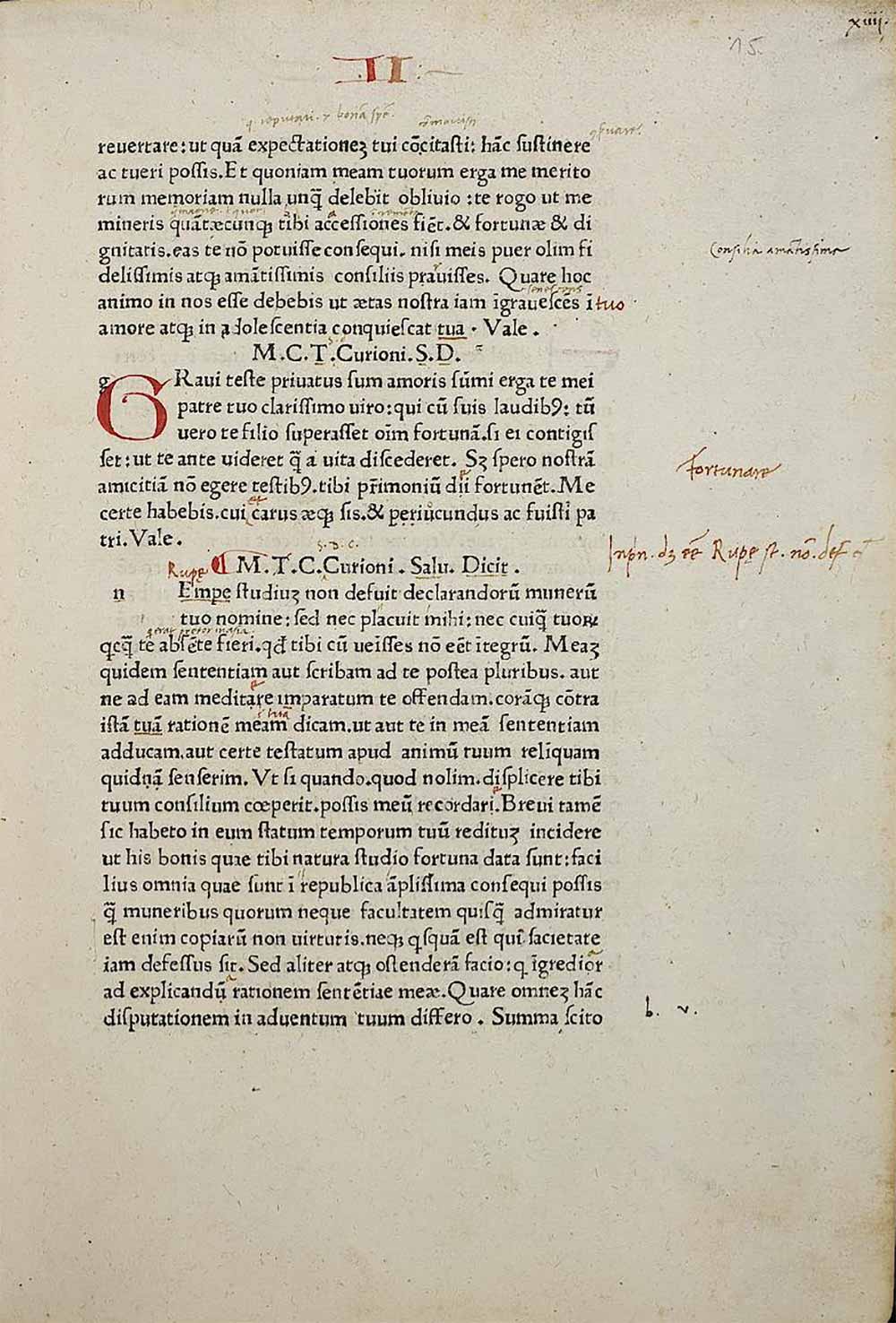
Nebenschriftgruppe, die im Sinne der typografischen Schriftklassifikation zur Schriftuntergruppe (Schriftart) Renaissance-Antiqua (Mediaeval, Old Style, Old Face) gehört, welche wiederum zur Hauptschriftgruppe Antiqua zählt; rundbogige Druckschrift römischen Ursprungs mit Serifen.
In der Paläografie und in der typografischen Literatur wird die Venezianische Renaissance-Antiqua auch als »Litterae Venetae« oder »Venezianische Antiqua«, im angelsächsischen Sprachraum (GB, USA etc.) als »Humanist« 1) oder »Venetian Oldstyle« bezeichnet.
Etymologie
»Venezianisch« bezieht sich auf die Republik und Stadt Venedig im Nordosten Italiens an der adriatischen Küste. Venedig entwickelte sich in der Renaissance durch die Migration deutscher Prototypografen ab Mitte des 15. Jahrhunderts zu einem der wichtigsten europäischen Zentren der Typografie. 2)
Unter »Renaissance« wird eine europäische Kulturepoche verstanden, die sich durch die »Wiederbelebung« antiker Ideale – insbesondere in Philosophie, Literatur, Wissenschaft, Malerei und Architektur – auszeichnet. Der Ursprung der Renaissance liegt in Italien, insbesondere in Florenz, Venedig, Rom und Mailand. Die Kulturwissenschaft unterscheidet in Frührenaissance (ab ca. 1420), Hochrenaissance (ab ca. 1500) und Spätrenaissance (ab ca. 1520).
In der Frührenaissance entwickelte sich auch die Typografie durch die Erfindung Johannes Gutenbergs (um 1400–1468). Durch sie konnten von nun an Ideen und Wissen maschinell reproduziert werden, was einen radikalen multidisziplinären Strukturwandel zur Folge hatte, der alle westeuropäischen Zivilisationen innerhalb kürzester Zeit nachhaltig veränderte. Humanismus, Aufklärung, die Entdogmatisierung der Wissenschaft, Liberalisierung und Typografie sind deshalb untrennbar miteinander verbunden.
Etymologisch bedeutet Renaissance »Rückbesinnung, Wiederbelebung«, was aus dem frz. »renaissance« für »Wiedergeburt« zu frz. »renitre« für »wiedergeboren werden, aufleben« zu frz. »naitre« für »geboren werden »und« re-« für »wieder« stammt. In Deutschland ist der Begriff ab Mitte des 19. Jahrhunderts gebräuchlich, um kulturwissenschaftlich den Übergang vom Mittelalter zur Neuzeit zu skizzieren.
Die Bezeichnung »Antiqua« leitet sich etymologisch von der lateinischen weiblichen Form zu »antiquus« für »vorig, alt«, einer Nebenform von »anticus« für »der vordere« vom lateinischen »ante« für »vor« ab. Mit »Antiqua« ist somit die »alte Schrift« gemeint.
Der Begriff »Antiqua« wird als Terminus primär im deutschsprachigen Raum sowohl für die Schriftgattung als auch für eine Schriftart verwendet. Er bezeichnet ausschließlich eine Druckschrift. Vorlagen aus der Epigraphik und Kalligraphie werden in der Paläografie anders bezeichnet. Die Antiqua ist heute die führende Verkehrsschrift der westlichen Welt.
Typometrie
Die frühen Archetypen der Venezianischen Renaissance-Antiqua orientieren sich bis zum Ende der Inkunabelzeit im Jahr 1500 immer noch leicht an der Kalligraphie, was vermutlich darauf zurückzuführen ist, dass die Prototypografen potentielle Käufer von kostbaren Büchern nicht durch die noch junge »Deutsche Kunst« (Typografie) abschrecken wollten. 3) Denn die Leser orientierten sich höchstwahrscheinlich mehrheitlich an den gewohnten Buchschriften, insbesondere an der Textura, die heute in der Paläografie als die höchstentwickelte kalligraphische Buchschrift der Gotik gilt, gefolgt von der Rotunda (Rundgotische Schrift), der »Gotico Cursiva« (Gotische Kursive) und diversen »Bastarda-Schriften« (Misch-Schriften). 4)
Die Formgebung der Buchstaben der Venezianischen Renaissance-Antiqua und ihre Anmutung wirken bis zur Schöpfung der »Aldinischen Antiqua« (Bembo-Type) noch sehr rudimentär. Die Kehlungen der Serifen und die der Dachansätze sind stark gerundet und die Oberlängen der Minuskeln ragen – wie auch bei der späteren französischen Variante – über die H-Höhe hinaus. Die Majuskeln »A« und »M« haben bei manchen historischen Varianten doppelseitige Kopfserifen; oder die Majuskel »A« besitzt einen kreisförmigen, nach innen geneigten Dachansatz oder einen überstehenden Scheitel.
Wobei jedoch zu erwähnen ist, dass die originalen »Litterae Venetae« im Hochdruck sehr viel klarer und besser auf dem Papier stehen, als ihre digitalen Remakes im Offsetdruck, beispielsweise die »Stempel Schneidler« (1939) von Friedrich Hermann Ernst Schneidler (1882–1956) als PostScript Font.
Die digitalen Nachbildungen imitieren zwar die alten Schriftstempel der Frührenaissance, berücksichtigen aber in der Regel nicht die Produktionstechniken jener Zeit (Anpressdruck, Farbkonsistenz, Papierbeschaffenheit, Wegschlagverhalten usw.). Deshalb haben digitale Remakes 5) und Formvarianten 6) – philologisch und ästhetisch betrachtet – mit den originalen Drucktypen im Auflagendruck meist wenig Gemeinsamkeiten. Ebenso sind die »fetten Auszeichnungsschnitte« eine Erfindung der Neuzeit.
Die wichtigsten Klassifikationsmerkmale 7) 8) einer Venezianischen Renaissance-Antiqua:
- Dachansätze der Minuskeln: Schräg
- Minuskeloberlängen: Über die H-Linie bis zur k-Linie
- Achse der Minuskel e: Schräger Innenbalken nach links geneigt
- Optische Achse der Rundformen: Teilweise stark nach links geneigt
- Serifenübergänge: Rund bis konisch